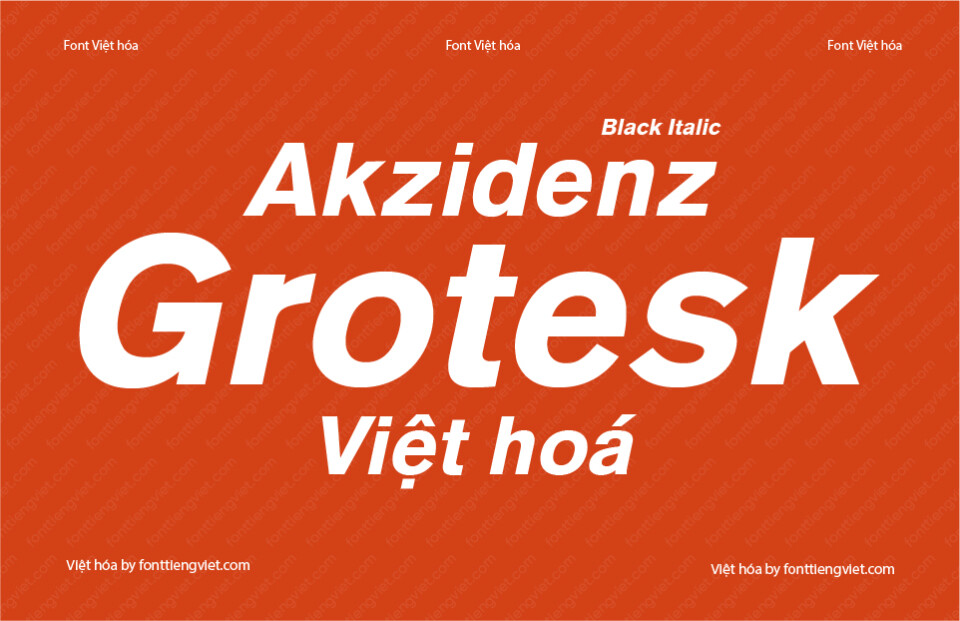
Font Việt hóa 1FTV VIP Akzidenz Grotesk Black Italic
Giới thiệu về Font Việt hóa 1FTV VIP Akzidenz Grotesk Black Italic
Trong thế giới đồ họa hiện đại, việc tìm kiếm một bộ chữ vừa mang tính lịch sử vừa đáp ứng được yêu cầu kỹ thuật khắt khe là điều không hề dễ dàng. Font Việt hóa 1FTV VIP Akzidenz Grotesk Black Italic chính là giải pháp hoàn hảo cho những nhà thiết kế đang tìm kiếm sự mạnh mẽ và cá tính. Đây là phiên bản được tối ưu hóa đặc biệt cho tiếng Việt từ bộ font huyền thoại Akzidenz Grotesk, giúp người dùng tại Việt Nam dễ dàng ứng dụng vào các dự án truyền thông và giáo dục mà không lo lỗi hiển thị dấu câu. Khi bạn sử dụng Font Miễn Phí để sáng tạo, giá trị thẩm mỹ của tác phẩm sẽ được nâng lên một tầm cao mới nhờ sự chỉn chu trong từng nét vẽ.
Lịch sử và nguồn gốc của bộ font kinh điển
Akzidenz Grotesk được biết đến là tiền thân của nhiều bộ font không chân (sans-serif) nổi tiếng thế giới. Với phiên bản Black Italic, độ dày và độ nghiêng của chữ tạo nên một cảm giác chuyển động không ngừng, rất phù hợp cho các tiêu đề cần sự chú ý ngay lập tức. Việc sở hữu Font Việt hóa 1FTV VIP Akzidenz Grotesk Black Italic không chỉ đơn thuần là cài đặt một tệp tin, mà là bạn đang mang cả một di sản thiết kế vào trong máy tính của mình.
Đặc điểm nổi bật của Font Việt hóa 1FTV VIP Akzidenz Grotesk Black Italic
Điểm khác biệt lớn nhất của phiên bản này chính là sự tinh tế trong việc xử lý các ký tự có dấu. Các dấu thanh trong tiếng Việt thường gây khó khăn cho các font chữ phương Tây, nhưng với Font Việt hóa 1FTV VIP Akzidenz Grotesk Black Italic, mọi thứ đều được căn chỉnh hài hòa, giữ nguyên tỉ lệ vàng của bộ chữ gốc. Độ đậm (Black) giúp chữ nổi bật trên các nền phức tạp, trong khi độ nghiêng (Italic) mang lại vẻ năng động, hiện đại và tràn đầy năng lượng.
Ứng dụng trong giáo dục và học tập
Đối với các bạn học sinh và sinh viên, việc sử dụng font chữ này trong các bài thuyết trình hay thiết kế poster sự kiện trường học sẽ tạo ra ấn tượng chuyên nghiệp. Font chữ này giúp các thông điệp quan trọng trở nên dễ đọc và thu hút thị giác hơn. Ngoài ra, các thầy cô giáo cũng có thể dùng nó để làm nổi bật các đề mục lớn trong giáo án điện tử, giúp học sinh dễ dàng theo dõi bài giảng một cách trực quan và sinh động nhất.
Lưu ý khi phối hợp font chữ
Vì đây là kiểu chữ rất đậm và nghiêng, bạn nên kết hợp nó với những font chữ mảnh hơn hoặc có chân (serif) để tạo sự cân bằng. Đừng nhồi nhét quá nhiều chữ trong một không gian hẹp, hãy để Font Việt hóa 1FTV VIP Akzidenz Grotesk Black Italic có khoảng trống để “thở”, từ đó phát huy tối đa hiệu quả thị giác mà nó mang lại cho bản thiết kế của bạn.
Kết luận về bộ Font Việt hóa 1FTV VIP Akzidenz Grotesk Black Italic